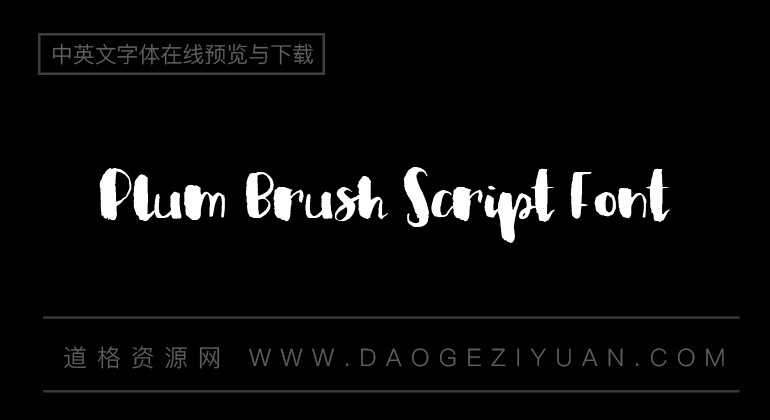
Plum Brush Script Font
Plum Brush Script 是一款手写风格的字体,具有非常自然、轻松和精细的线条。它的笔画仿佛是由毛笔书写而成,带有一定的笔画变化和不规则性,使得每个字母都具有独特的个性和风格。 该字体适用于多种设计场景,如印刷品、海报、广告、包装等。它可以用于设计标语、标题、品牌标志等,能够营造出温馨、自然、亲切的感觉,同时也能够增加设计作品的艺术感和美感。 Plum Brush Script 字体支持多种语言,具有很好的可读性和易用性。它的特点在于呈现出手写的感觉,使得设计作品更加具有人情味和生动性。
Plum Brush Script Font是一款非常不错的手写艺术字体,具有很好的视觉感,适合于文化类的宣传设计、商业类品牌的广告和产品包装设计以及个性化文字排版等较多场景。